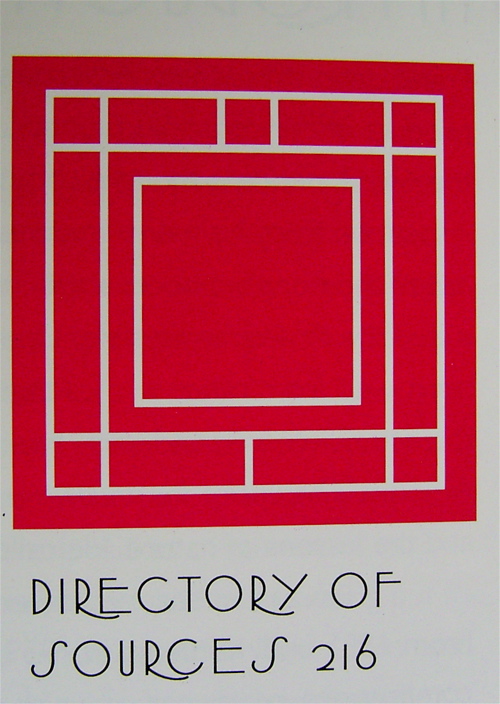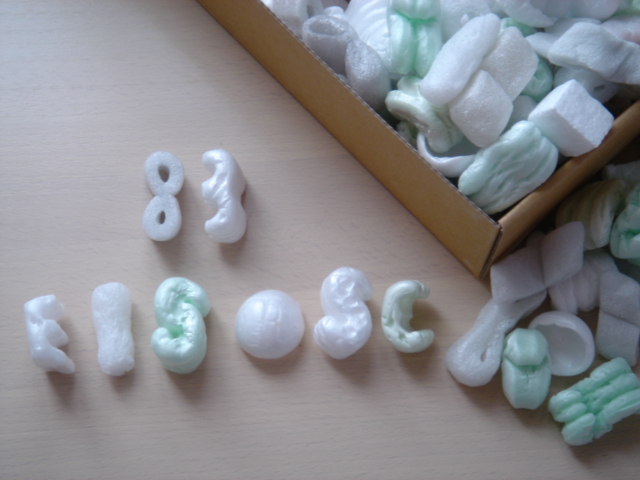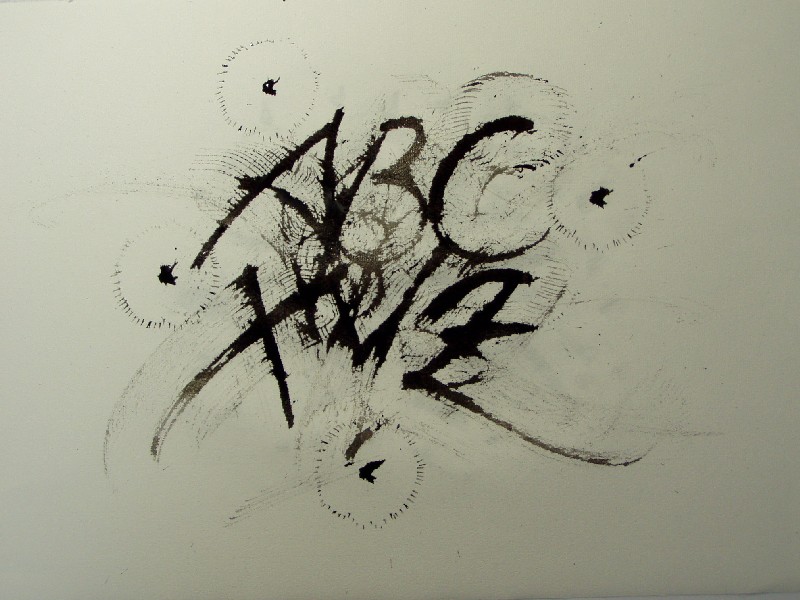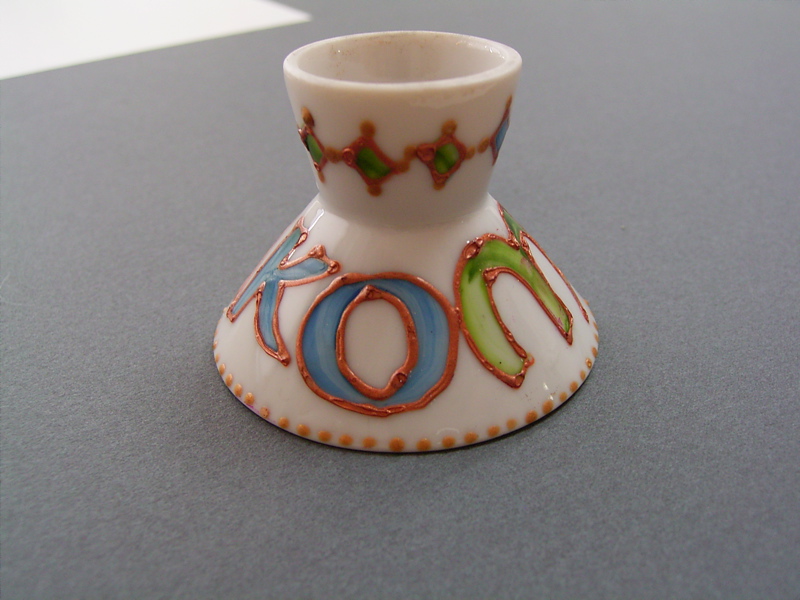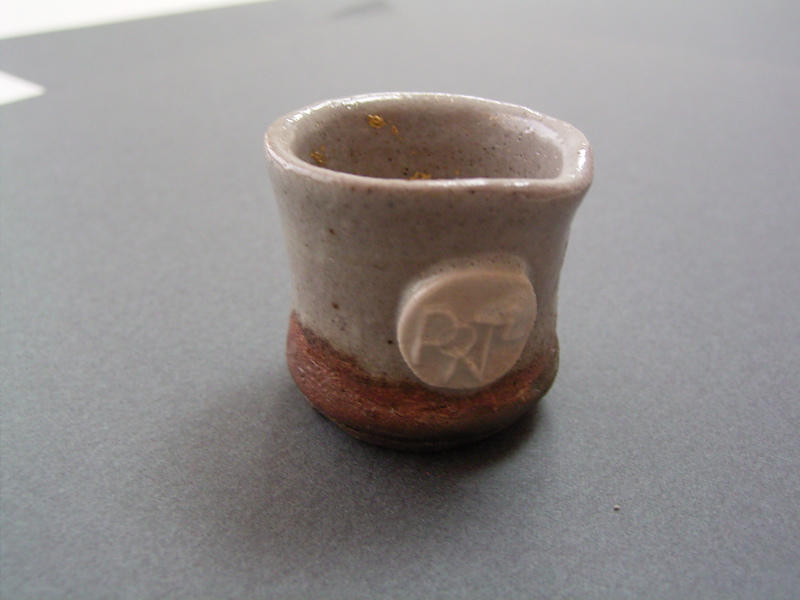
フランクロイド ライトと漏電ブレーカ
昨日のクラスで、フランクロイドライトのデザインを参考にする方がいらっしゃったので、昔アメリカにいた頃に買った本を引っぱりだしてきました。
今までゆっくり見たことがなかったその本の目次に、こんな素敵なデザインが!
内装、ステンドグラス、家具などに使われている形。シンプルなマークとしても素晴らしい! いいなぁ・・・・としみじみ見ていたら、んんんん・・・???またまた、いつもどこかで見た様な・・・・・?
あたりを見回したら、部屋の隅っこの高いところに見〜つけた!電気のブレーカのデザインが、なぜかとっても似ているじゃない・・・・・・(画像では、ライトのデザインに挟まれているのがブレーカです)
なぜブレーカーのスイッチの横にこのような隙間のある窓?が存在するのか、皆目検討はつきませんが、いずれにしても、このブレーカの制作会社「河村電機産業株式会社」!
なかなかいいデザインですよ!
皆様のお宅のブレーカ、同じデザインでしょうか?
インク入れ
文字を書く時に、器用にインクをスポイトで、毎回ペンに入れて書く方法を取る方が多くいらっしゃいますが、私はその細かい作業がどうも苦手で
、インク瓶へそのままペン先を突っ込んでしまいます。でも瓶の形によっては、使いにくい時があります。そんな時活躍するのが、これ!どちらもインク入れとして毎日活躍しています。左は、私がまだアメリカに住んでいた頃に、最初にカリグラフィーを教えてもらった先生から名前入りで頂いた もの。shrift shop(中古品やガラクタの様な物を売っているお店)で見つけたお猪口に、陶器用の絵の具で名前と模様を書いてオーブンで焼き付けて作ったそうです。
それにしても、お猪口を逆さまにするこの発想! 安定していて、インク入れとしてこれ以上の物はないほどピッタリです。もっと欲しくて日本でも探していま すが、陶器でこの形のお猪口って見かけません。私は、お酒はほとんど飲めないなのでよくわかりませんが、最近はぐい呑みが一般的なのでしょうか??
右は、福岡でカリグラフィーの教室とグループ「スタジオ・ポンテ」を主催していらっしゃる初島さつきさんからいただいた物です。陶芸家のご主人様の作だそうです!ちゃんと、「Ponte」をいうロゴが入っています。底の部分がずっしりと重くなっているので、安定していて使いやすいです。
野口みずきさんに会いたかった!
野口みずきさんがベルリンマラソンで日本記録を達成して優勝しました。
この夏サン・モリッツを訪れ、野口みずきさんがトレーニングしている町だと知りました。写真のフィールドでは他にも
たくさんのアスリートがトレーニングをつんでいる様子が見られました。私達はちょうどフィールドの前にあるホテルに滞在したのでした・・・。確かに日本の
報道関係の人も見たので、野口さんは毎日トレーニングしていたのでしょう。あ〜なのに、なのに残念!
その姿に出会えることはありませんでした・・・。でも同じ空気を吸っているんだなぁ〜と思っただけでちょっと感動ものでした。
背後にスキー場のある山々がそびえているので、散策も出来ます。ゴンドラで山頂まで行き、そこから徒歩で降りてくる のが楽な方法・・・。山を降りきって、民家の間を散策していたら、こちらを見つめている視線に気づき・・・「?」な〜んだ、かめさんがこちらに挨拶してた んですね・・・。「なぜ、かめさん?」それはわかりませんが、ご主人様の愛情で幸せそうに置かれていました!
・・・やっぱり、野口さんの走る姿見たかったなぁ・・・。練習でもすっごく速いんでしょうね〜。
コロボックル ディクショナリー
だいぶ前に画材屋さんで見つけた可愛いデザインのクリアファイル。色やコラージュしたテクスチャーが私好みで、作者は一体誰なんだろう、と思っていましたところ、先日、「遊べる本屋」で元の本を発見しました!
その名も「コロボックルディクショナリー」
外国の童話作家なのかなーと思っていたら、日本人の「colobockle」さん(絵本&クラフト作家で活躍されている立本倫子さんという方)でした。
この本はディクショナリーということで、アルファベットのAからZまでが可愛いイラストや写真、そして詩で構成されています。
例えばAならAcorn(ドングリ)とか、GならGiraffe pencil case(きりんのペンケース)の作り方とか、ひとつひとつがとても面白い! ページもカラフルで何度見ても飽きません。子供と一緒に見ても楽しいと思います。おすすめです!
コロボックルディクショナリー曼珠沙華
毎年、彼岸の頃になると、家の近くの傾斜地に決まって咲く、赤い花を楽しみにしています。夏の間まで、ただ緑の草だけだったはずの場所に、突然のように現れるすっくとたったその赤い姿に、9月なんだなあと、感傷でいっぱいになります。幼い頃、遠い昔の記憶でしょうか?遠いところ逝ってしまった人に思いを馳せるからでしょうか?
曼珠沙華の呼び名は、天上の紅い花を意味するそうですが、彼岸花のほかに、天蓋花、死人花、狐花、幽霊花、とうろう花、捨子花など千種類もの呼び名があるそうです。ラテン語の学名は、Lycoris radiata、リコリスという響きは、和名とは違ったしなやかな趣を感じます。英名の呼び名も何種かあり、Cluster amaryllis-群生するアマリリスは、情緒のない名前?!Red spider lilyは、イメージ的?!赤い蜘蛛とは、確かにそんな風体、 Hurricane lilyも台風の時期にあいますね。でも、やはり、和の呼び名は、叙情豊かで、ちょっと怖いながら、繊細な感性を感じて素敵です。
山頭火の句が沁みます。
かたまって曼珠沙華のいよいよ赤く
曼珠沙華咲いてここが私の寝るところ
悔いるこころの曼珠沙華燃ゆる
この花が、緑のみに姿をかえ、赤い記憶が封印されると、金木犀の香りがただよう秋のはじまりがやってきます。
ふかふかABC
腰痛が治ってきたので片付けものをしていましたら、以前「ジョン・ニール ブックセラー」で購入したときの段ボール箱が出てきました。 フタを開けるとパラパラと梱包材が落ちてきて。いくつかのアルファベットや数字のように見える(そのもの?)がありなかなかキュートです。
こんなところに までアルファベットが使ってあるなんてすてきな遊び心だなあ、と思いながら箱の中に手をつっこんでみたのですが・・・何もない・・・梱包材が入っているだ けだったのです。
たしかインクを買ったような記憶があるのですがそのインク自体は一体何処に?
ふかふかクッションだけ引越しで運んできたのですねえ、なにもかも記憶の彼方 とはまた悩みが増えました。
イエローバンド
今日は、イエローバンドをご紹介します。
フランスで7割近くの人が視聴するといわれている自転車レース「ツール・ド・フランス」。長い伝統を誇る自転車レースは欧米で大変な人気があり、その中で1999年から今年2005年まで前人未到の7連覇を達成したのがアメリカ人のランス・アームストロングです。彼は伝説の人となりました。アームストロングのもう一つの伝説は彼が癌に侵され死の直前から生還してのこの偉業達成であるということです。彼は癌治療の間に、癌と戦う人のために「ランス・アームストロング財団」を設立しました。
私は高校時代、癌に侵されたクラブの後輩をほんの数ヶ月で失いました。学生時代の友人も癌でこの世を去りました。それは風にさらわれたかのようなあっという間の出来事だったのです。何も出来なかった自分を後悔していました・・・。
ほんの少しのことから始めることが出来たら・・・、そんなきっかけを与えてくれたのが、アームストロングの活動でした。イエローバンドを購入すると寄付金として活動の資金となります。
カリグラフィーのブックマーク
私が文字が好きな事を知っている友人は、外国旅行のお土産には必ず文字入りの何かを探して来てくれます。その中でも本のしおりはお手頃なのでよく頂く事が多く、ずいぶんカリグラフィーのブックマークが増えました。
イギリス、アイルランド、イタリアなどヨーロッパのお土産では、写本や装飾文字など歴史のある文字やデザインが多いですね。アメリカでのカンファレンスで配られるGoody Bag(福袋の様にいろいろなお楽しみのグッズが入っている)でもらうものは、アメリカ各地にあるカリグラフィーのギルドやグループが独自に作っているものが多くて個性豊か。どちらも素敵!
私のお気に入りは、ピサの斜塔のデザインのブックマーク。固めのヴェラム(仔牛の皮)にプリントされていますが、ウルトラマリンの色がとても鮮やかです。文字もバーサル体で書かれていれ本当に綺麗。形も変わっていて、なぜか下がガタガタとした階段状になっています。
沢山あっても、実際こういう本のしおりは、時々眺めてみるコレクションとして引き出しにしまわれています。でもこれからは読書の秋。見るだけでなく、思い切って使ってみようかしら?
モジトルワークショップ報告
9月19日(月)の祝日に、モジトルワークショップ第1弾、「ゴールド探検ブック」を開催致しました。
モジトルメルマガ登録者限定のワークショップでしたが、多数のお申し込みを頂き、定員一杯でご参加頂けなかった方もいらっしゃいました。ゴメンナサイ!
今回、このワークショップのためにモジトルメンバーがかき集めた金色の画材、総数ナント!43種類!オオオッ!!
その43種類を、長〜いアコーディオンブックにサンプルとしてまとめました。参加者はそれぞれのブックと筆を持ってグルグルとテーブルをまわり、金色を試しました。
金色と言っても、その色や質感はそれぞれのメーカーや材料によってかなり違います。私たちモジトルメンバーにとっても、初めて手に取る画材もあり、あっという間の2時間半でした。最後はカバーにリボンをつけてハイ出来上がり!
茶せんの運命
「ご自宅用ですか?」「・・・そ、そうです。」慣れないお店で茶せんを購入しました。しかし、自宅で抹茶を頂くのではありません・・・。表千家の「お」ぐらい習った私にとって、茶せんは抹茶シャカシャカのリズムより、紙の上でシャッシャッのリズムの方がいいかも・・・という気持ちになったのでした。
巧みの技で作られた竹の穂先はよくさばけていて、しなりも抜群です。墨を入れた容器をシャカシャカ・・・。高い茶碗も袱紗も要りません。「結構なお手前」は「大胆な筆さばき」取って代わって紙の上を面白い線が行きかいます。しかもこれ「あなた絶対に茶せんでしょう!」という痕跡を残します・・・。
まだまだ始めたばかりのツールなので、今後この茶せんがどんな風に化け化けしていくのか楽しみです。しかもこのツール自分で立ってくれるので筆置き要らずだった・・・。自立するツール!!偉いぞ〜!